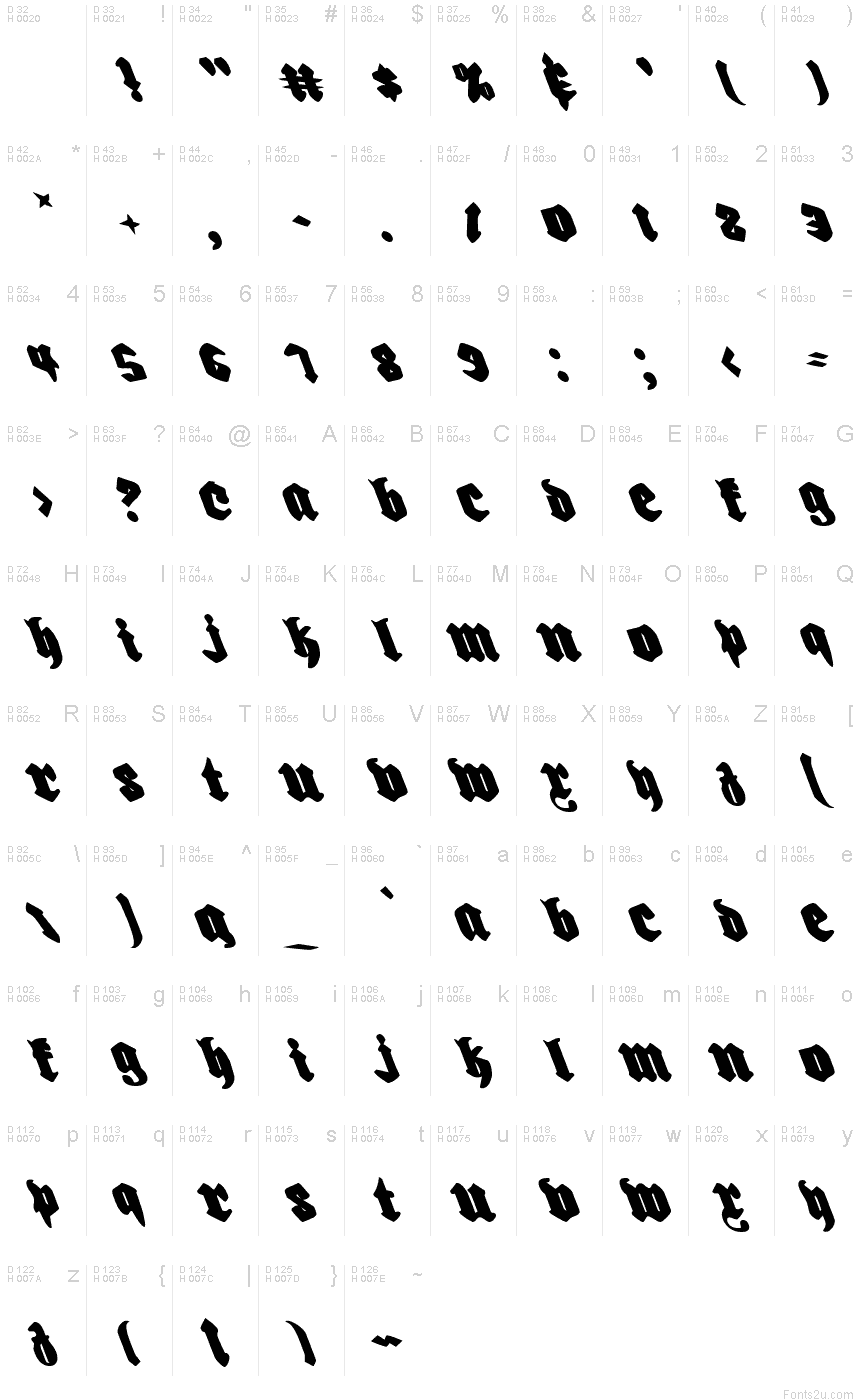
Biergarten Leftalic od Iconian Fonts to darmowy średniowieczny gotycki krój pisma w piwiarnianym klimacie. Litery opierają się na bazie blackletter, ale są zmiękczone, bardziej pogodne i masywne, z ciężkimi, zaokrąglonymi kształtami i nierównym rytmem, który przywołuje klimat dawnych czasów, nie będąc przy tym surowym.
Sprawdzi się na plakatach Oktoberfestu, w brandingu pubów, na etykietach piwa, ulotkach czy w menu, gdzie ten nieco «zakrapiany» średniowieczny klimat szybko nadaje charakteru. Jako darmowy font, świetnie nadaje się też do nagłówków, krótkich haseł i grafik na gadżety, zwłaszcza gdy szukasz gotyckiego kroju, który jest bardziej świąteczny i przystępny niż dostojny.
Biergärten Leftalic